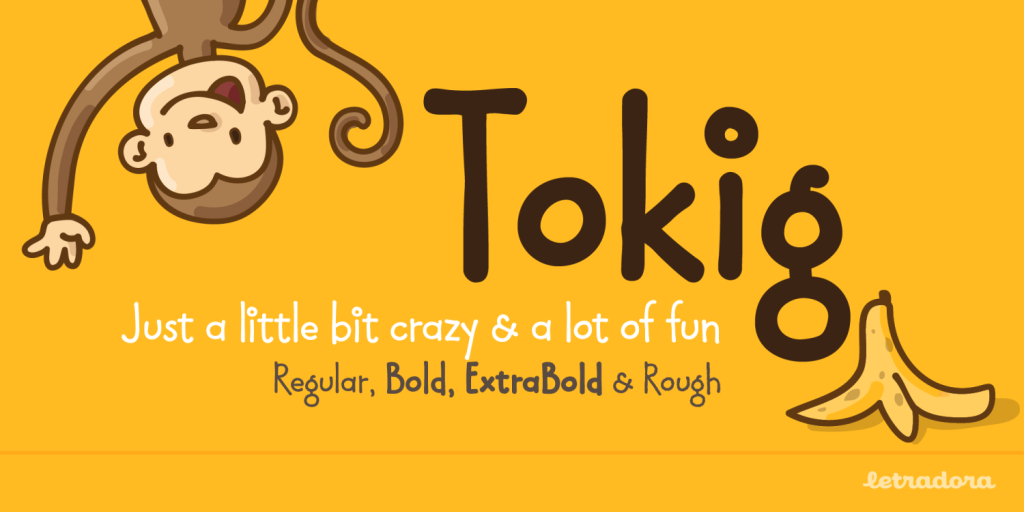
Tác giả: Kemie Guaida
Font SVN TokigPx thuộc bộ font SVN đây là một kiểu chữ độc đáo, mang phong cách hiện đại và phá cách, thích hợp cho các dự án thiết kế đòi hỏi sự sáng tạo và nổi bật. Với các nét chữ mạnh mẽ, táo bạo và cấu trúc hình học đặc trưng, font SVN TokigPx thường được sử dụng trong thiết kế logo, poster, hoặc các ấn phẩm quảng cáo. Font chữ này giúp tạo ấn tượng mạnh mẽ và thu hút sự chú ý ngay từ cái nhìn đầu tiên. Nếu bạn đang tìm kiếm một font chữ đầy cá tính và khác biệt, font SVN TokigPx sẽ là lựa chọn tuyệt vời để mang lại sự mới mẻ cho thiết kế của bạn.